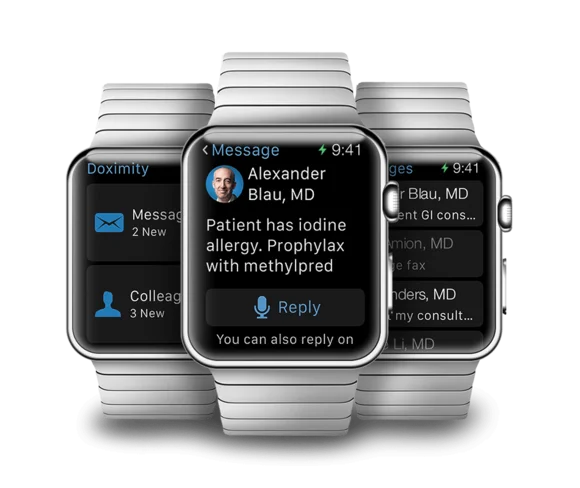
Come anticipato, sui prossimi iOS 9 e OS X 10.11 Apple probabilmente sostituirà il font di default Helvetica Neue con il San Francisco già in uso su Apple Watch.
Una scelta che va a migliorare la leggibilità in parte persa con il precedente cambio font avvenuto con iOS 7 che, con l’Helvetica Neue, puntava tutto sulle linee pulite. Il San Francisco, lo ricordiamo, è tra le altre cose il carattere usato per le serigrafie sui nuovi MacBook (Apple ha abbandonato il vecchio ‘VAG Rounded’).